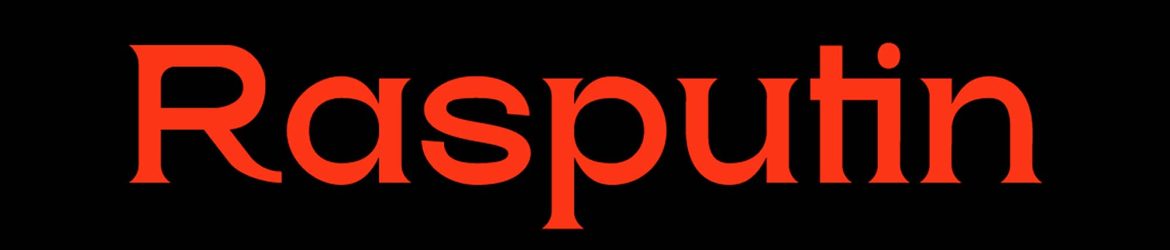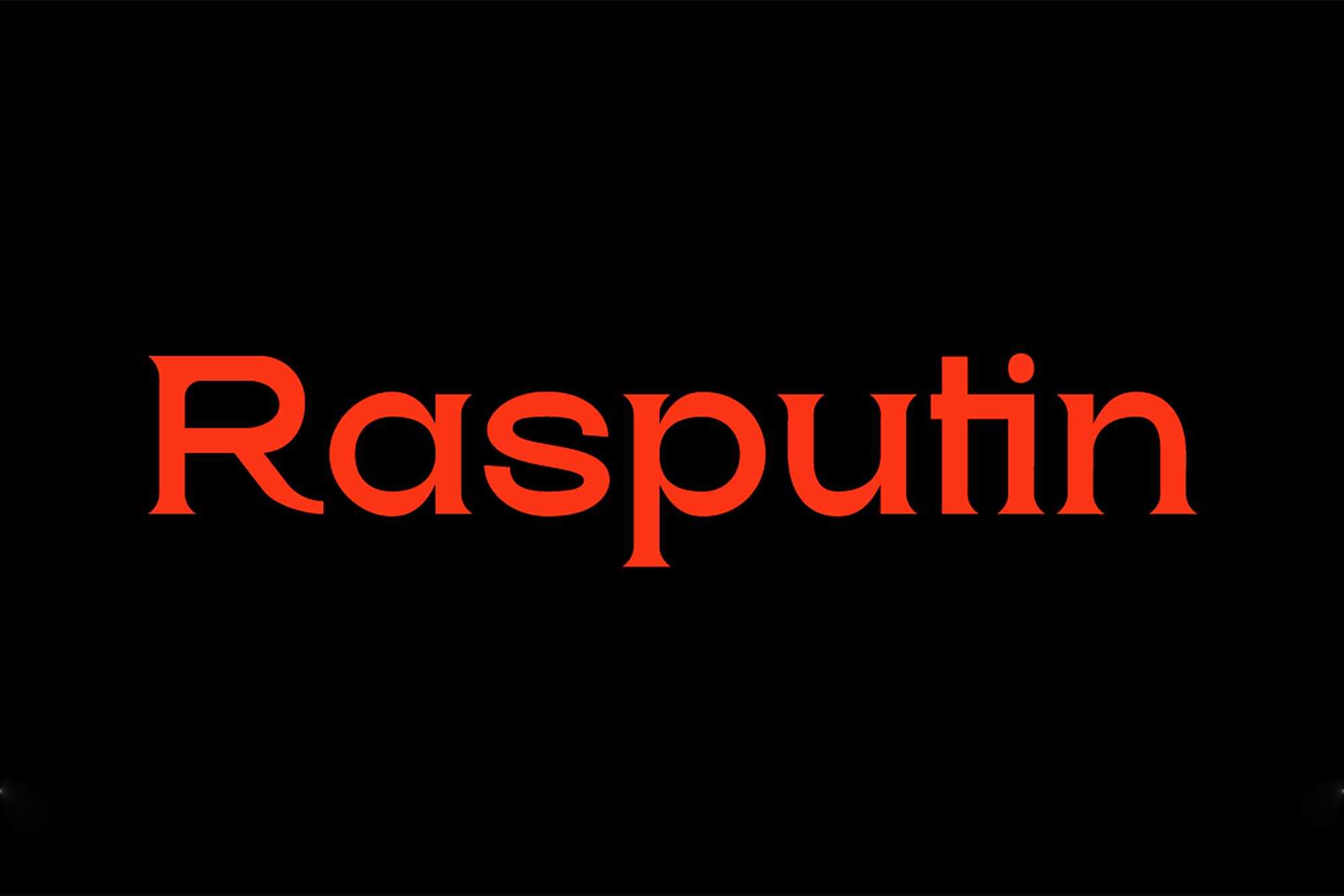
Rasputin Serif Font
Rasputin Serif é uma fonte que parece estar sempre em um enigma, rodeada de mistério. Sua história e desaparição, que até hoje soa como uma narrativa fictícia, causam uma mistura de confusão e entusiasmo. Este recurso gráfico traz à vida uma fonte que, assim como Rasputin, ainda nos deixa em dúvida e nos faz sonhar com seu legado. Rasputin é parte integrante da mitologia russa, e isso é algo que a fonte Rasputin Serif também carrega consigo. Ela é um recurso gráfico que convida os designers a experimentar e desvendar esse enigma de fonte. Seja para criar anúncios, capas de livros ou até mesmo e-mails, a fonte Rasputin Serif pode revolucionar suas criações, deixando-as mais únicas e intrigantes.